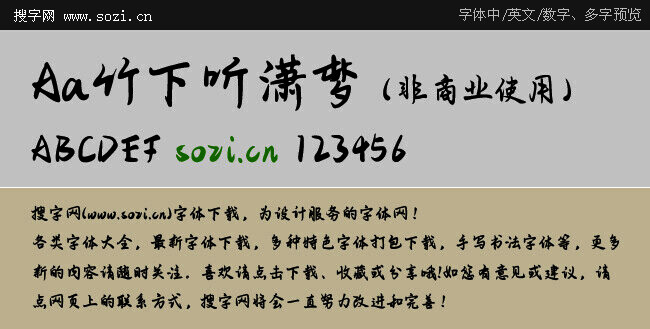
Aa竹下聽(tīng)瀟夢(mèng)
搜字網(wǎng)給大家提供一款A(yù)a竹下聽(tīng)瀟夢(mèng)(非商業(yè)使用)中文字體下載,該字體是一款中文手寫書法字體,字體書寫自然優(yōu)美,筆畫流暢,結(jié)構(gòu)肆意灑脫,具有很好的視覺(jué)感。適合圖書設(shè)計(jì)、包裝設(shè)計(jì)、海報(bào)設(shè)計(jì)等應(yīng)用(此字體為個(gè)人非商用版,商用可以聯(lián)系QQ:1006760504)。